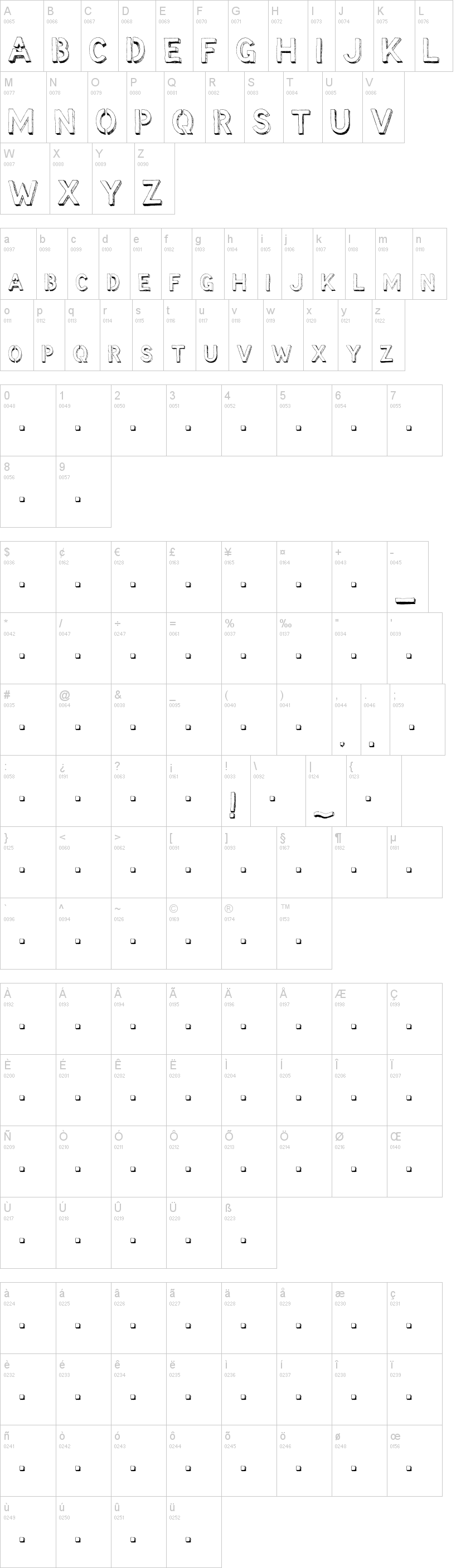
McCoy字体是一种经典的英文字体,由英国设计师John McCoy在20世纪30年代创造出来的。McCoy字体的特点是字母的几何形状,细节丰富,拥有较宽的字符间距,具有清晰的视觉效果,使其在早期的印刷品中得到了广泛的应用。McCoy字体的字形极具灵活性,可以适应不同的文字风格,可以用于印刷品、网页设计、平面设计等多种应用场景。内容介绍
McCoy - Hello Lori是一款非常不错的手写艺术字体,具有很好的视觉感,适合于文化类的宣传设计、商业类品牌的广告和产品包装设计以及个性化文字排版等较多场景。